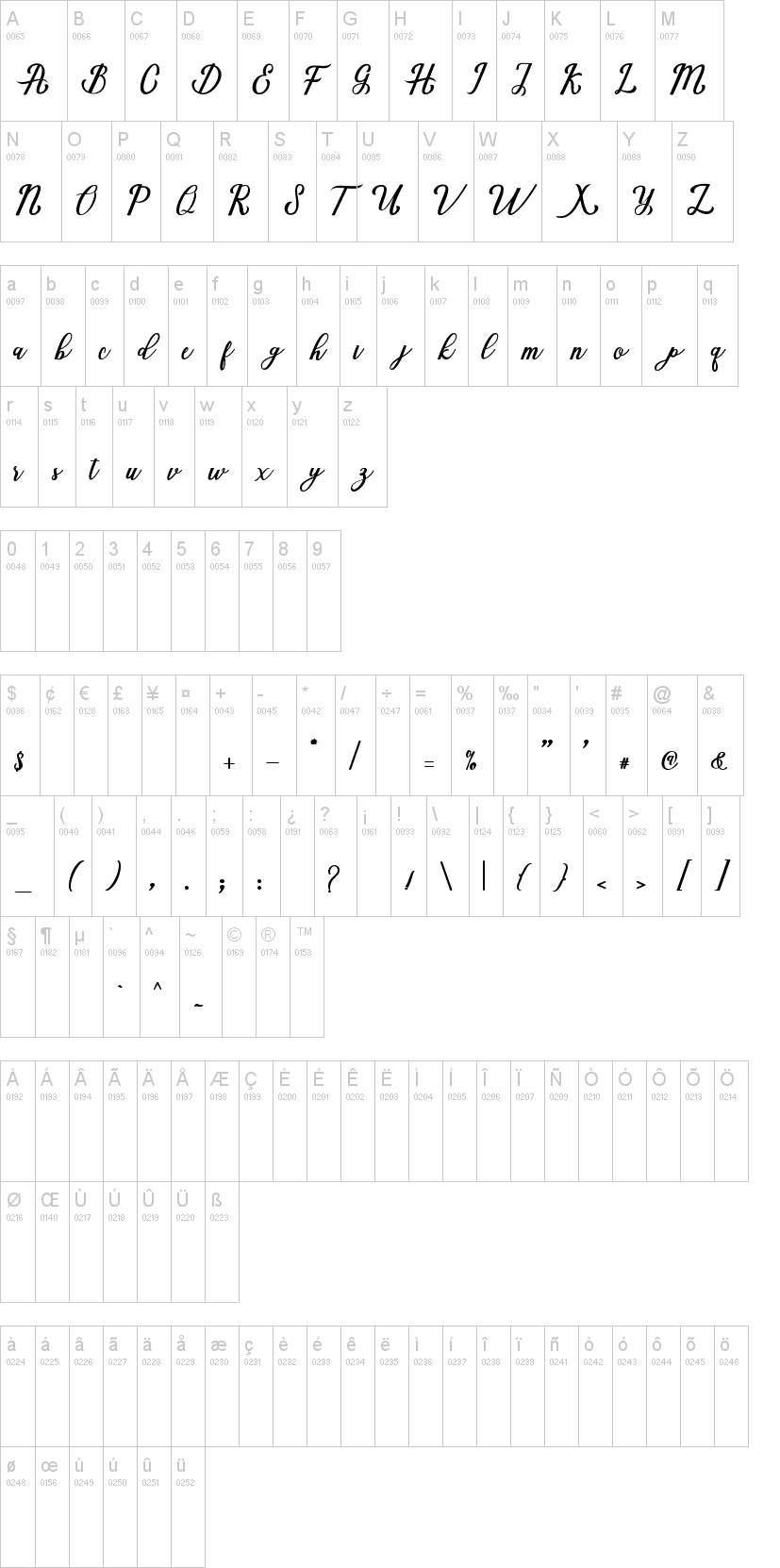
Marija Script 是一款自由的脚本字体,由著名的设计师Marija Vidovic设计,它具有自然的流动性,可以用于许多不同的设计项目,从印刷到网络设计,它都可以满足你的需求。Marija Script包含了所有常见的字母,数字和符号,以及一些非常漂亮的上标和下标,它可以帮助你轻松地创建流畅的文本,使你的设计更加有趣。内容介绍
Marria Script是一款非常不错的手写艺术字体,具有很好的视觉感,适合于文化类的宣传设计、商业类品牌的广告和产品包装设计以及个性化文字排版等较多场景。